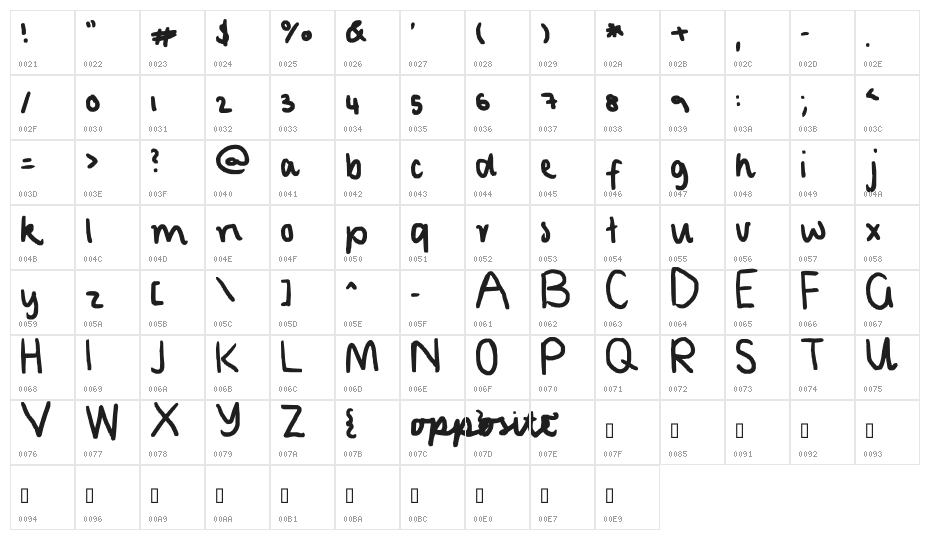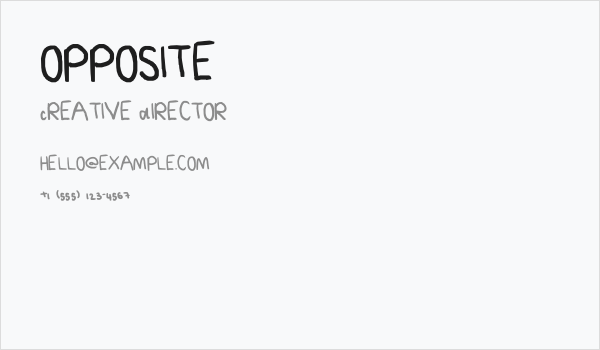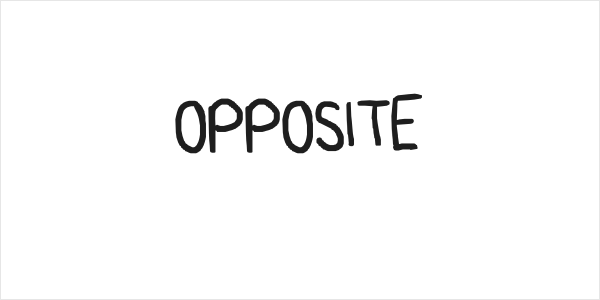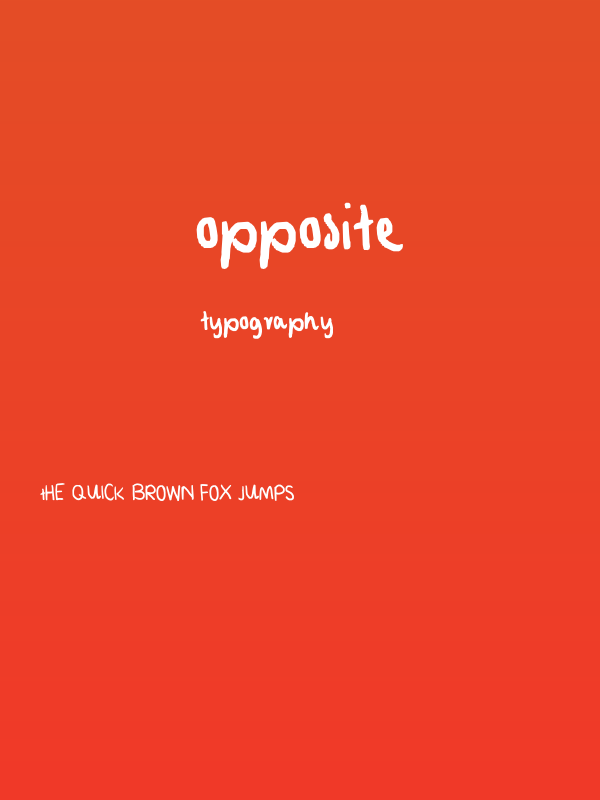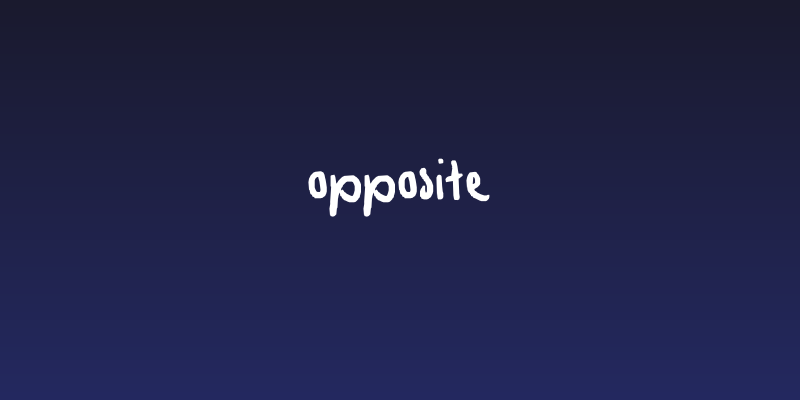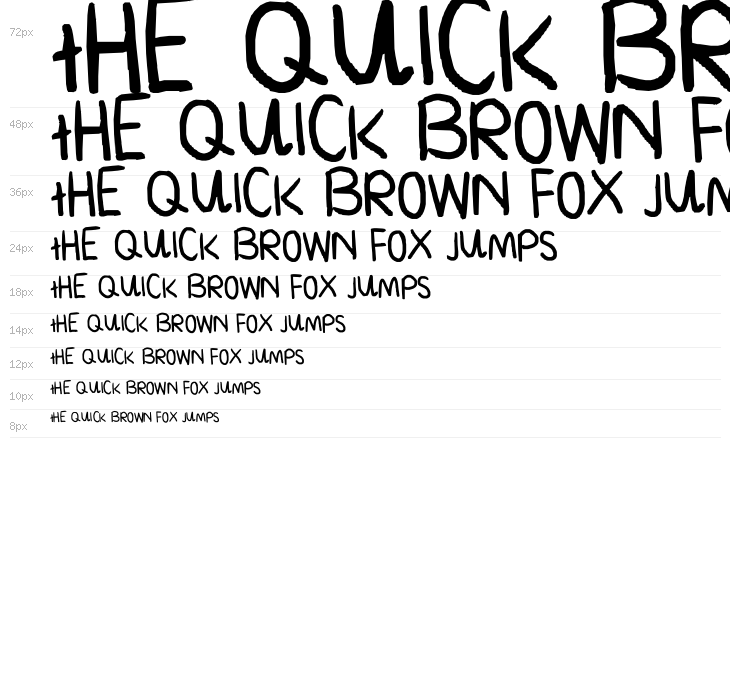
opposite Font
| النمط العام | Casual, Playful |
| حالة الاستخدام | Headlines, Informal text, Creative projects |
| مشاريع مقترحة | Ideal for children's books, greeting cards, personal blogs, and creative projects that require a casual and approachable feel. |